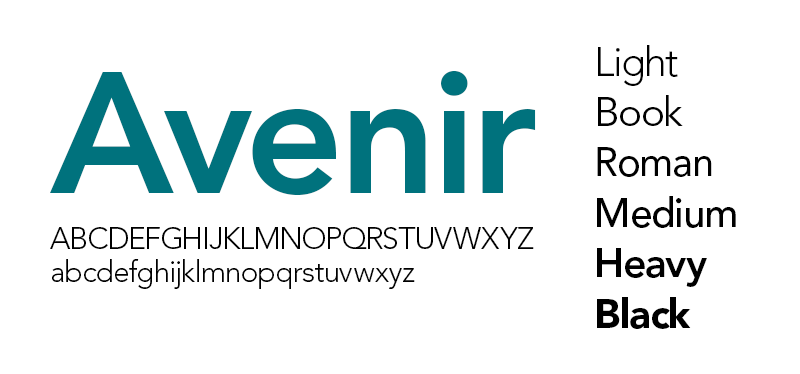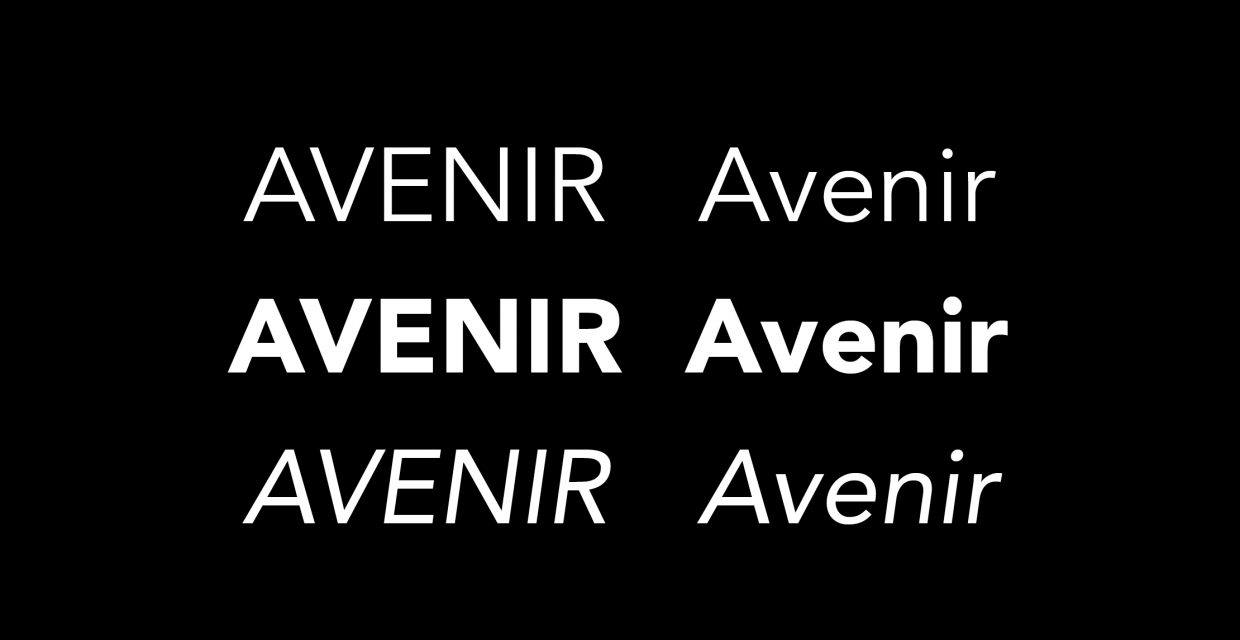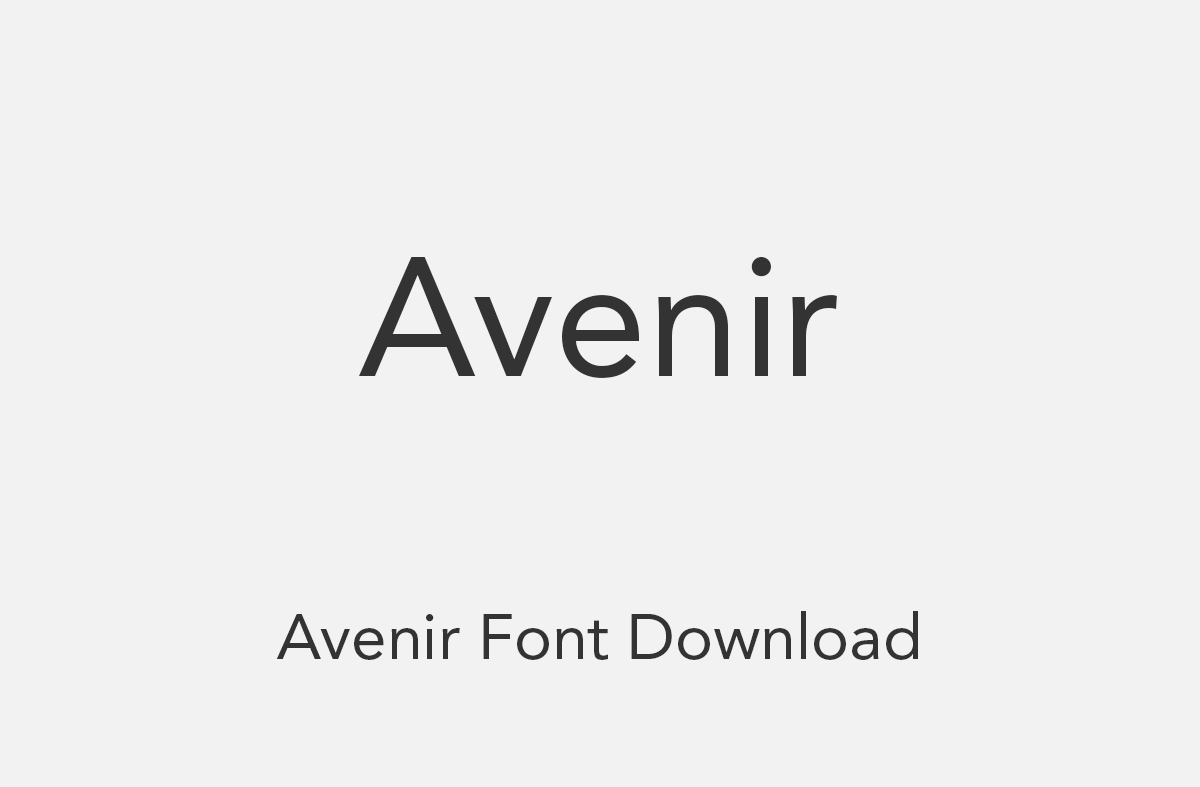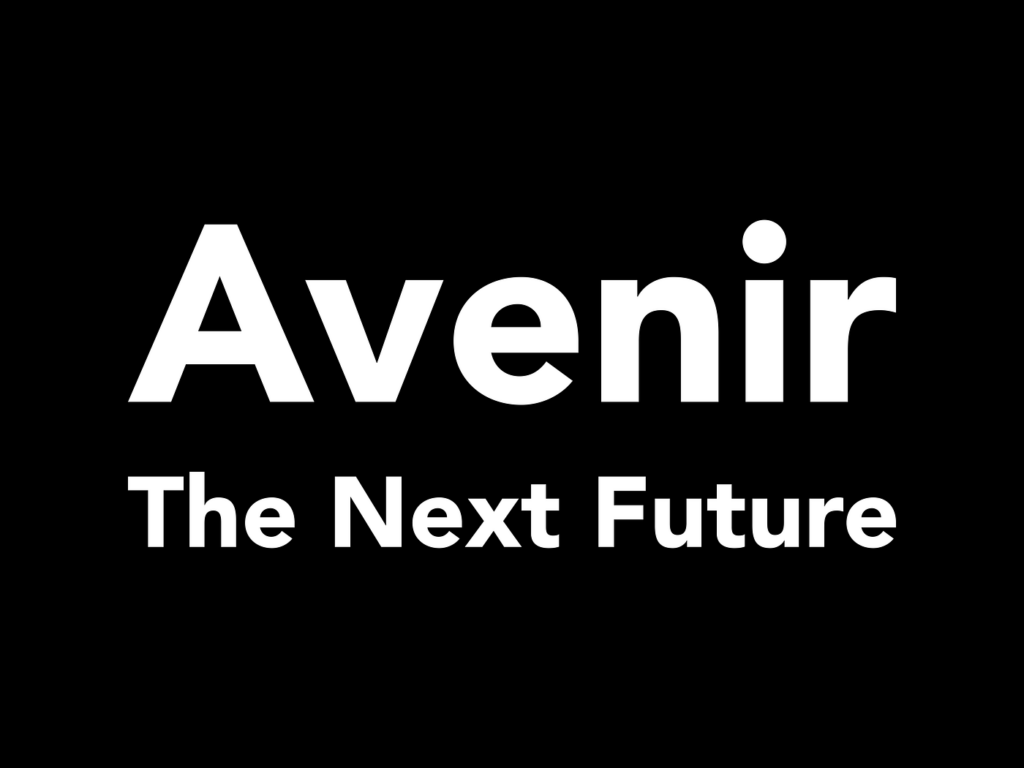
Avenir là một trong những bộ phông chữ Sans-serif kinh điển được thiết kế bởi Adrian Frutiger vào năm 1988. Tên gọi “Avenir” trong tiếng Pháp có nghĩa là “tương lai”, phản ánh đúng tinh thần hiện đại, sạch sẽ và bền vững mà bộ chữ này mang lại. Việc sử dụng font Avenir Việt hóa giúp các kiến trúc sư và nhà thiết kế trình bày các bản thuyết minh dự án, bộ nhận diện thương hiệu công trình một cách chuyên nghiệp, tránh các lỗi hiển thị ký tự đặc trưng của tiếng Việt.
Đặc điểm thẩm mỹ và cấu trúc của font Avenir Việt hóa
Các đường nét của Avenir sở hữu sự cân bằng về trọng lượng nét, giúp văn bản trở nên thông thoáng và cực kỳ dễ đọc trên cả màn hình kỹ thuật số lẫn bản in. Phiên bản font Avenir Việt hóa đã xử lý tinh tế hệ thống dấu thanh, đảm bảo các ký tự đặc thù như “đ, ă, ơ” phối hợp hài hòa với khung chữ chính, duy trì nhịp điệu thẩm mỹ xuyên suốt của bộ gốc.
Sự ổn định của bộ phông này còn thể hiện ở dải biến thể vô cùng phong phú, từ phiên bản Avenir book font download nhẹ nhàng đến các kiểu chữ đậm dày dặn. Đặc biệt, gia đình font Avenir Next mang đến những cải tiến về không gian ký tự, giúp tối ưu hóa khả năng hiển thị ở nhiều kích cỡ khác nhau. Đây là giải pháp phù hợp để truyền tải tư duy thiết kế hiện đại, tinh gọn, rất ăn ý với các phong cách kiến trúc tối giản và các giải pháp xây dựng lắp ghép thông minh hiện nay.
| Phân loại phong cách | Geometric Sans-serif / Modern Style |
| Bảng mã hỗ trợ | Unicode chuẩn toàn cầu |
| Các dòng tiêu biểu | Avenir, Avenir Next, Avenir Next Condensed |
| Mục đích phù hợp | Branding, Hồ sơ kỹ thuật, Website, Poster |
Tư vấn trình bày: Để bản thiết kế đạt được hiệu quả thị giác ổn định, bạn nên sử dụng Avenir black font download cho các đề mục lớn để tạo độ nhấn mạnh mẽ. Trong khi đó, kiểu font Avenir Next Việt hóa dạng Regular hoặc Book sẽ là lựa chọn phù hợp cho phần nội dung thuyết minh chi tiết, giúp khách hàng dễ dàng tiếp nhận thông tin dự án.
03 Ứng dụng font Avenir Next vào thực tế công trình
Nhờ diện mạo khoa học và giàu tính thẩm mỹ, việc sử dụng các kiểu chữ từ gói Avenir Next font Việt hóa mang lại giá trị thực tế cao trong khâu quảng bá và hoàn thiện công trình:
- Hệ thống nhận diện cho Resort & Homestay: Những nét chữ thanh thoát của Avenir rất ăn ý khi xuất hiện trên biển hiệu mica gương hoặc inox phủ màu. Phông chữ này giúp không gian toát lên vẻ sang trọng, hiện đại và tạo ấn tượng về sự chuyên nghiệp cho du khách ngay khi bước chân vào khu nhà lắp ghép.
- Thiết kế sơ đồ chỉ dẫn nội khu: Sử dụng font Avenir Next condensed giúp các chỉ dẫn lối đi, tên phòng chức năng trở nên gọn gàng, tiết kiệm diện tích trên các bảng hiệu nhỏ nhưng vẫn đảm bảo sự minh bạch và rõ nét.
- Trang trí không gian nội thất tối giản: Bạn có thể dùng font Avenir để cắt chữ nổi laser trang trí tại sảnh chờ văn phòng container, tạo điểm nhấn hiện đại và khơi gợi cảm hứng làm việc năng động cho nhân viên.
03 Lưu ý về bố cục chuyên nghiệp với phông chữ Avenir
Để khai thác hiệu quả vẻ đẹp trung tính của dòng font Sans-serif đa năng này, người thiết kế nên lưu tâm một số lưu ý kỹ thuật sau:
- Kiểm soát khoảng cách dòng (Leading): Với cấu trúc chữ hiện đại của Avenir, bạn nên thiết lập khoảng cách dòng thoáng một chút (khoảng 1.4 – 1.5 lần cỡ chữ) để văn bản không bị bết dính, giúp người đọc cảm thấy thoải mái hơn khi tiếp nhận các tài liệu báo giá dài.
- Phân cấp thông tin bằng độ đậm: Hãy tận dụng biến thể Bold hoặc Black cho các con số quan trọng trong dự toán công trình. Điều này giúp các thông tin cốt lõi trở nên nổi bật mà không cần phải sử dụng quá nhiều màu sắc gây nhiễu thị giác.
- Tính đồng bộ trong hệ thống hồ sơ: Hãy duy trì sử dụng gia đình font Avenir xuyên suốt từ bản vẽ AutoCAD đến slide thuyết trình Powerpoint để tạo nên sự nhất quán và chuyên nghiệp trong hình ảnh thương hiệu của đơn vị thi công.